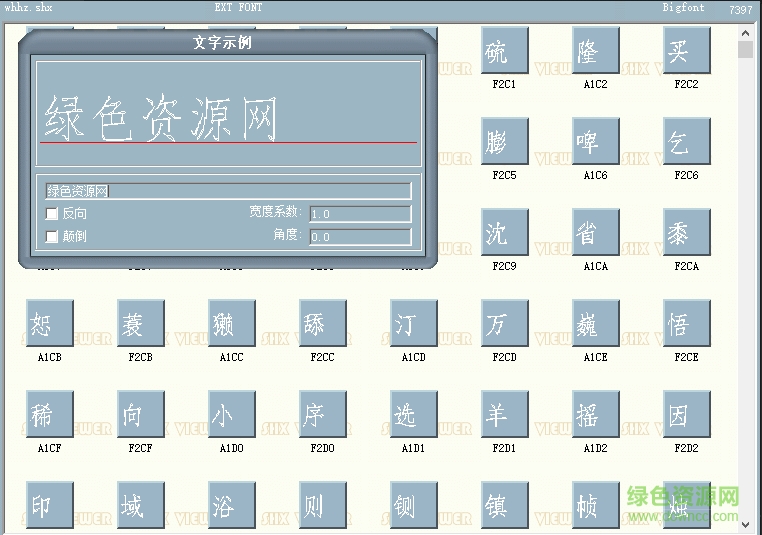
whhz字體是一款autocad必備的cad字體。當(dāng)電腦提示cad圖紙字體無法顯示時(shí),用戶需要下載這款字體。建議仔細(xì)閱讀安裝教程后下載。
1、在dwg文件的存儲上占用的空間小,在顯示的速度上比較快。特別是文字比較多的情況下,regen的重顯的速度上的差異更明顯,在實(shí)時(shí)移動(pan)的更新上不存在時(shí)差現(xiàn)象。
2、由于Windows字體為外來字體(相對于SHX字體),在生成及編輯的過程中,還不能做到完美無缺。比如,TrueType字體(Windows字體)的文字在移動、拷貝的過程中,句子的長度可能與實(shí)際的長度不同,影響了參考定位。再如,TrueType字體的實(shí)際高度可能與指定的高度之間有差異,不能精確地指定字高,只能通過試錯的方式確定,影響了繪圖的速度,也影響了編程控制的難度。
3、由于SHX字體為線型字體,可以像線段一樣指定特別屬性,產(chǎn)生特殊效果。比如,可以指定厚度值,從而產(chǎn)生立體效果。
4、與TrueType字體相比,SHX字體美觀效果不夠理想,但在工程中尚可滿足需要。SHX字體相當(dāng)于硬筆書法,在模擬毛筆書法上存有差距。